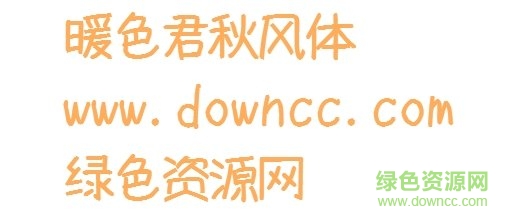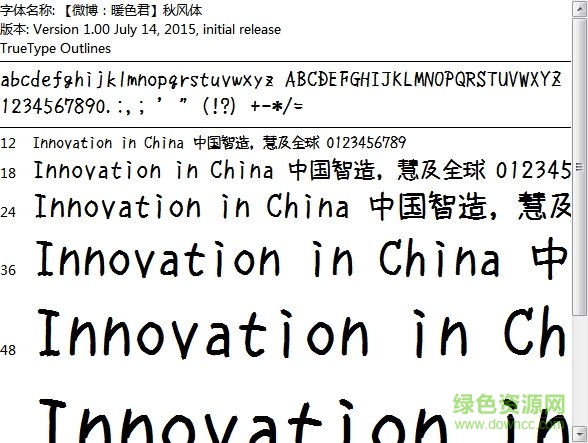
暖色君秋風(fēng)體是新浪微博暖色君推出的一款干凈清爽的手寫字體,造型清秀溫婉,給人秋風(fēng)寥落高遠(yuǎn)的特色視覺體驗(yàn),讓你的設(shè)計(jì)更有巧思,綠色資源網(wǎng)今日推薦!
秋風(fēng)體,由微博暖色君分享,字體結(jié)構(gòu)分明,無論中文還是英文都有自己的書寫特色,較常規(guī)字體更黑一些,讓視覺呈現(xiàn)更加顯眼,結(jié)合了手寫字體和書法字體的風(fēng)格,可以廣泛運(yùn)用于藝術(shù)設(shè)計(jì)、海報(bào)設(shè)計(jì)、名片設(shè)計(jì)等諸多場合。
暖色君秋風(fēng)體,也叫作暖色君的秋子體,是新浪微博字體達(dá)人暖色君分享的一款秋風(fēng)體字體,支持繁簡體輸入,自己秀氣柔美,給人秋季安靜恬適的獨(dú)特體驗(yàn),流暢的結(jié)構(gòu)和筆觸給你清晰的視覺閱讀感受。